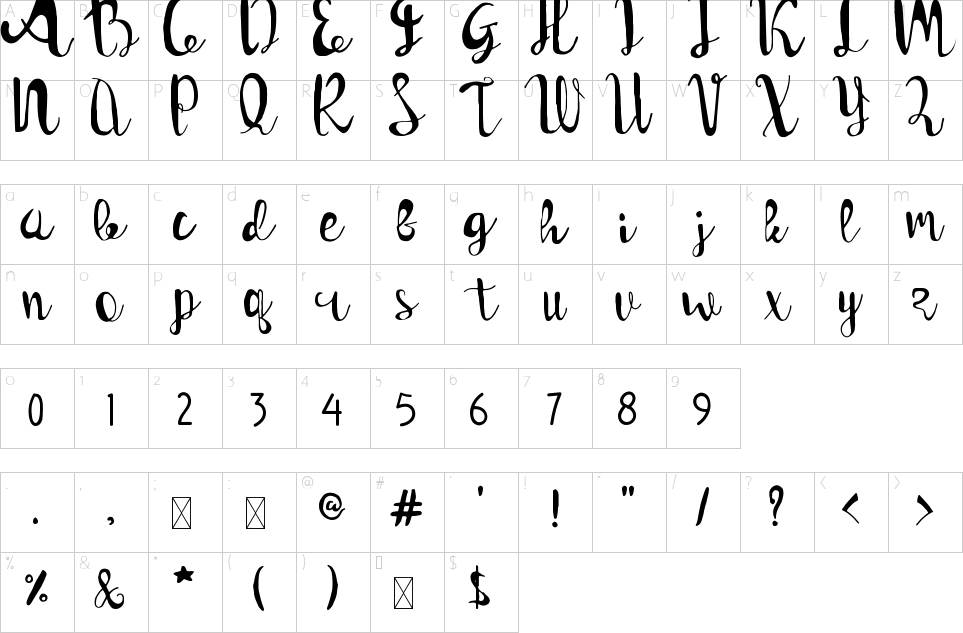
Aqui está uma descrição para a página de download da fonte ‘Genius Font’ na categoria de Fontes Grátis: Descubra a fonte Genius para dispositivos Windows e Mac, projetada pelo InermediaSTUDIO. Essa elegante fonte é perfeita para qualquer aplicação digital que exige uma aparência sofisticada e moderna. Designada especialmente para escrita legível em grandes tamanhos, ela pode ser usada tanto em materiais impressos quanto digitais, garantindo um visual atraente em qualquer projeto. Com downloads acima de 270 vezes confirmados, Genius está entre as opções mais populares e valorizadas nas fontes grátis disponíveis. Para quem busca uma solução eficaz para estilizar textos em formatos diversos, esta é uma ótima escolha. Experimente a diferença que Genius pode fazer em seu próximo projeto de design digital.